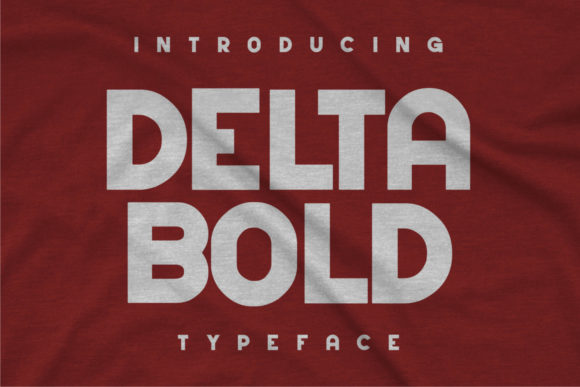
Название: Delta Bold Font (2021)
Delta Bold - это крутой, смелый и современный шрифт.
Этот шрифт идеально подходит для написания веб-дизайнов, визитных карточек и практически всего, что требует уникального штриха.